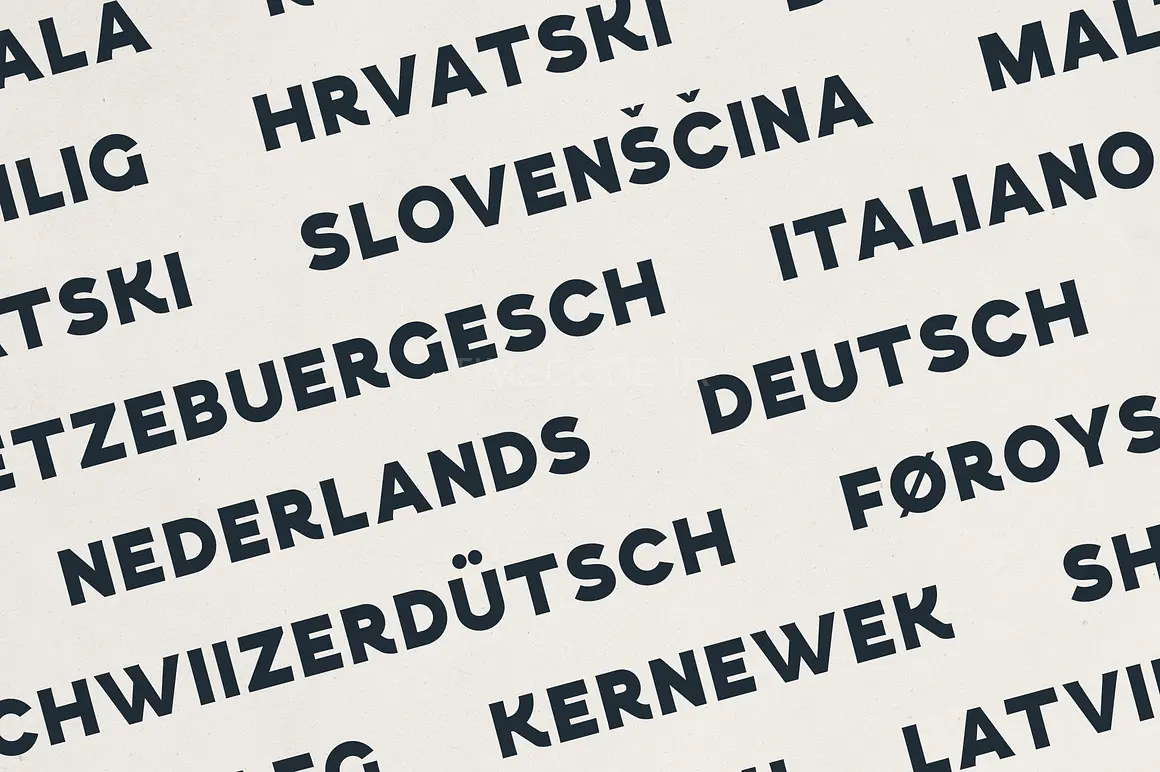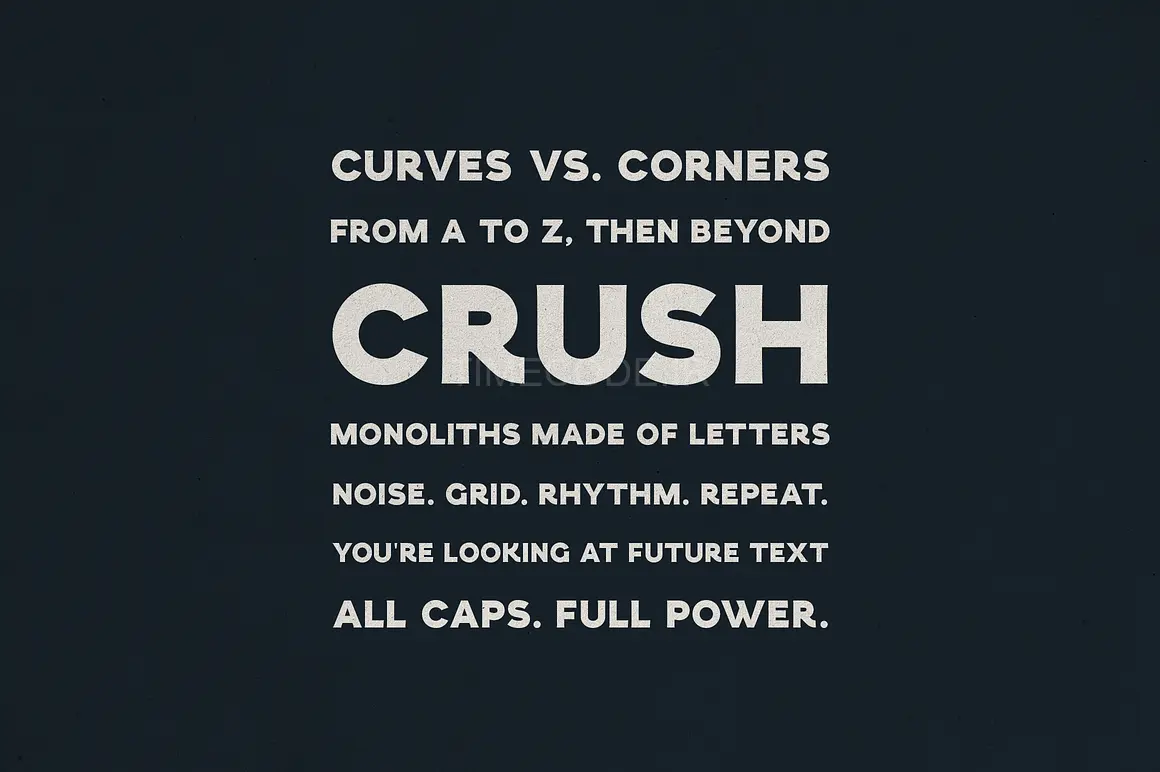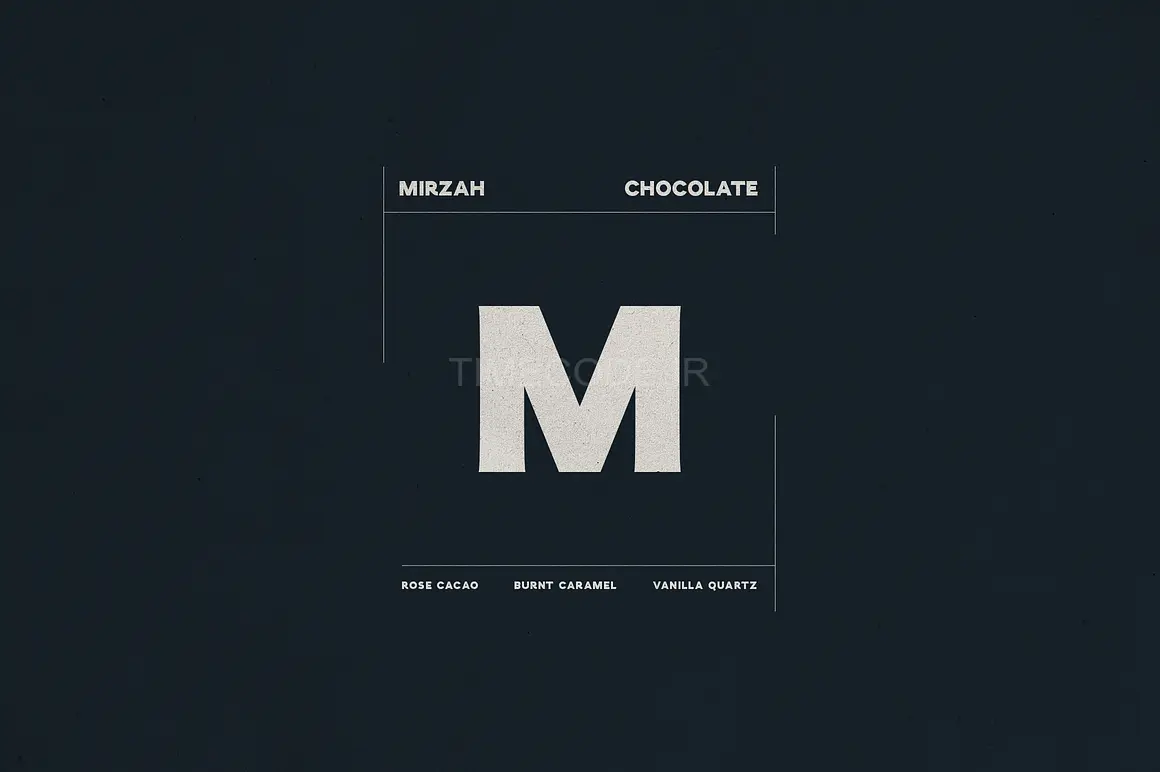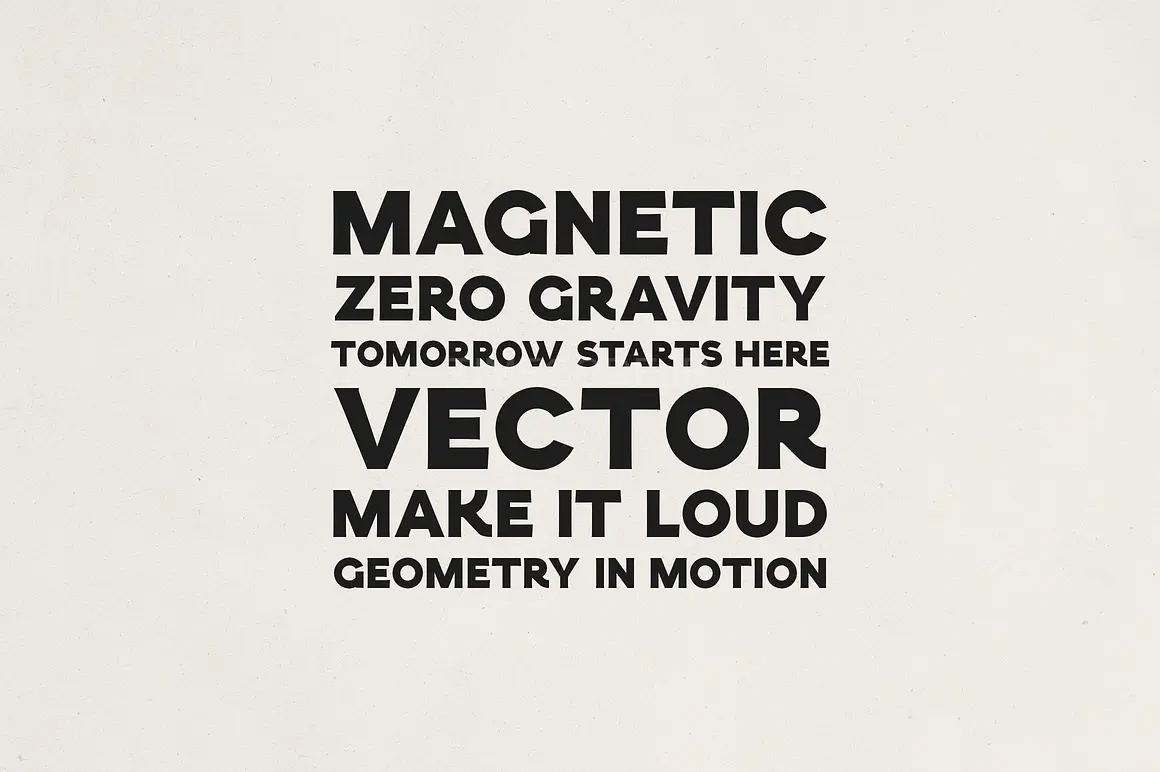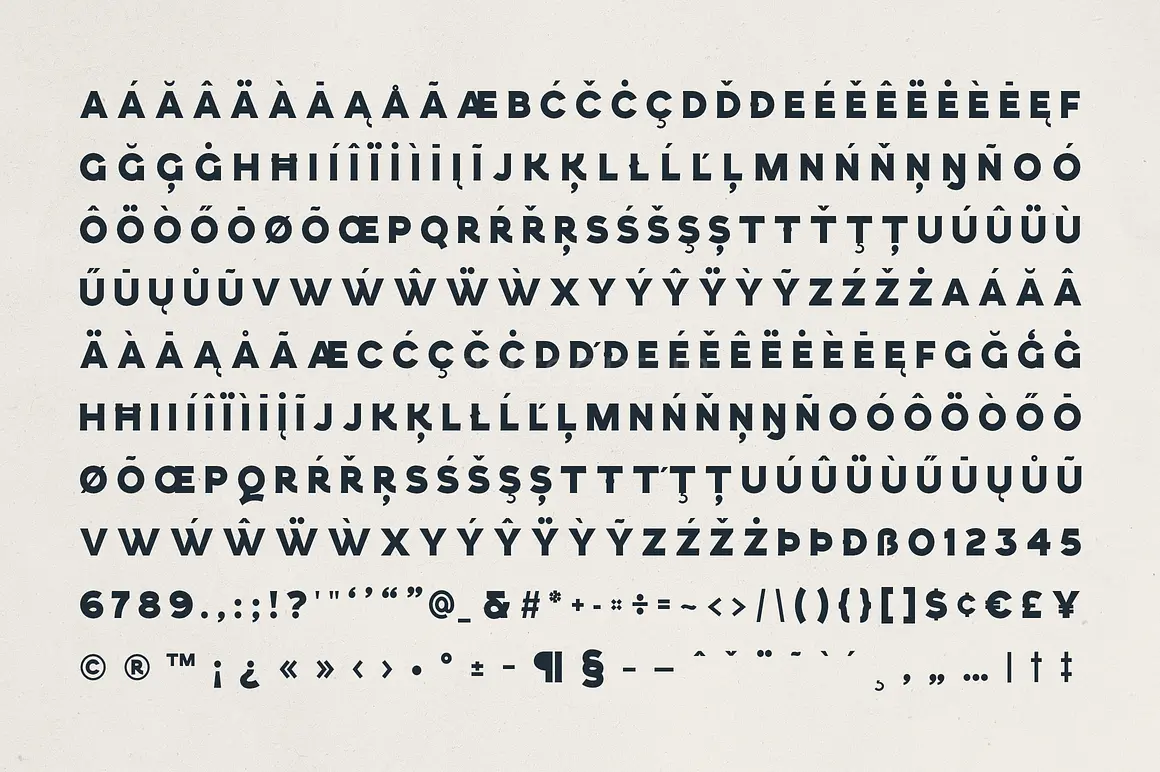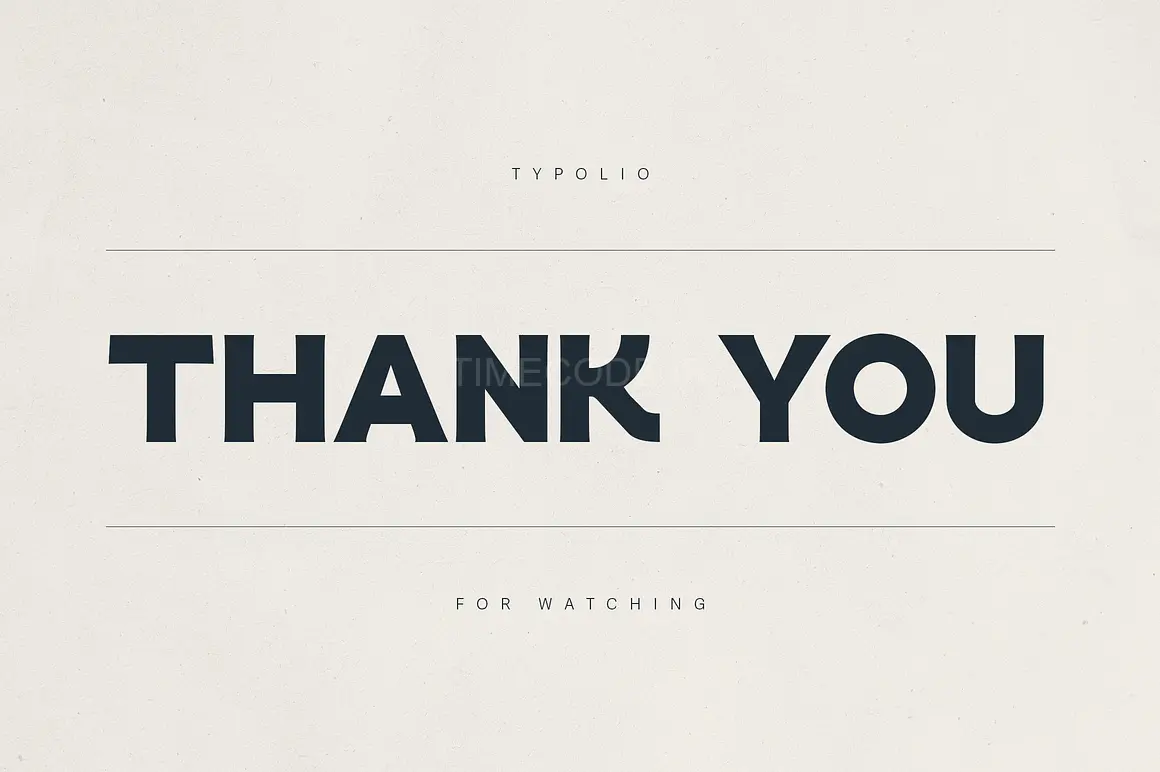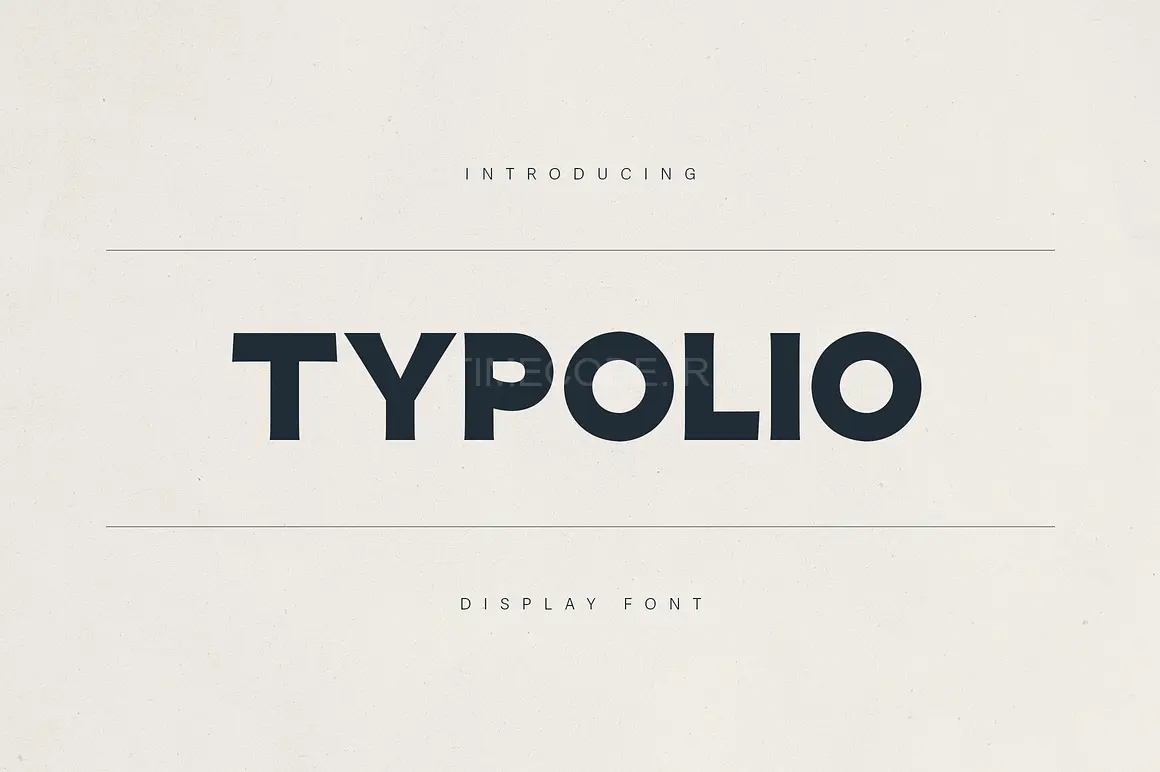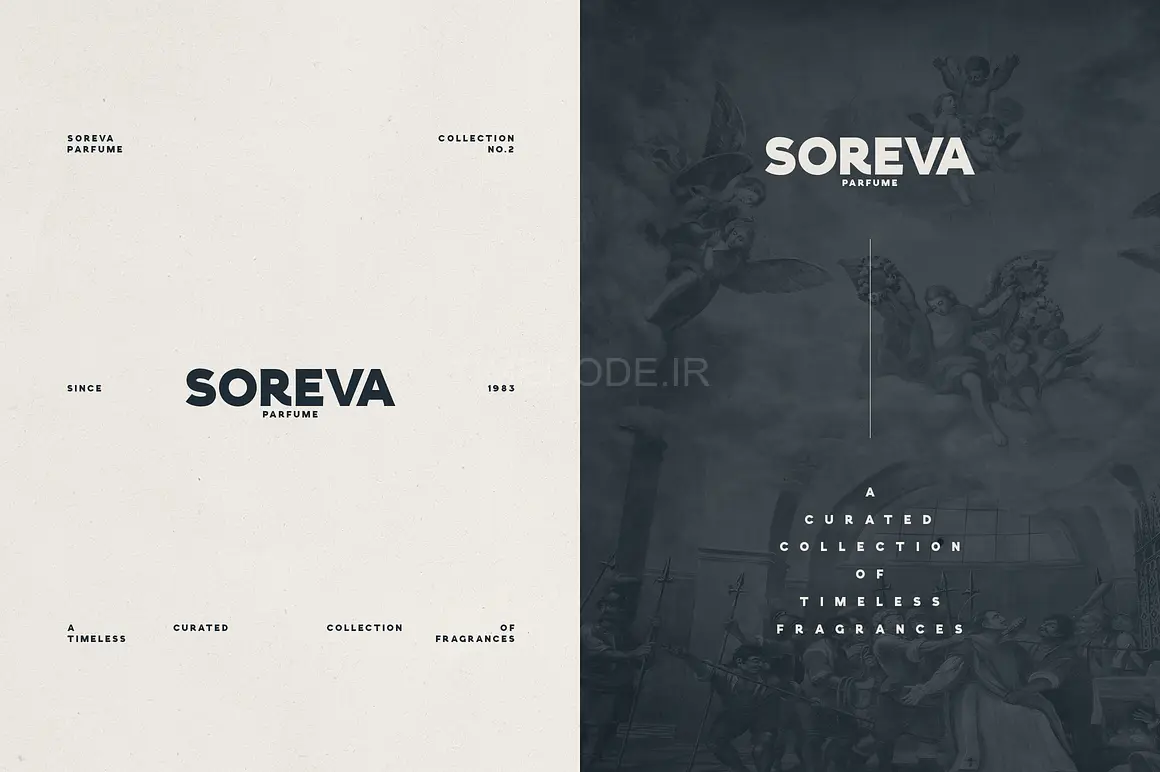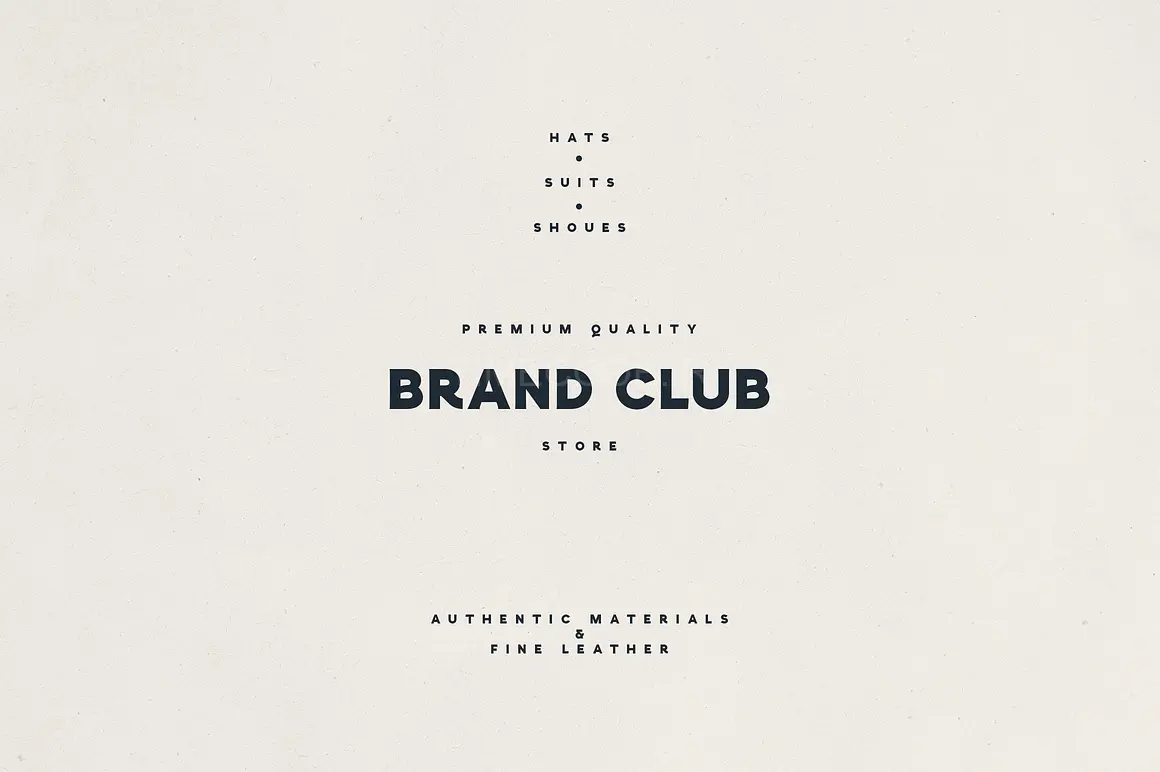
Typolio فونت نمایشگر جسور برای برندهای مدرن. یک فونت نمایشگر همه‌کاره و تأثیرگذار است که برای برندسازی جسورانه، سرفصل‌های مجلات، بسته‌بندی، و پروژه‌های طراحی معاصر طراحی شده است. Typolio با ساختار هندسی قوی و خطوط تمیز خود، سادگی مدرنیستی را با زیبایی‌شناسی سطح بالا ترکیب می‌کند – مناسب برای لوگوها، پوسترها، لیبل‌های مد، استارتاپ‌های تکنولوژی، و طرح‌بندی‌های مینیمالیستی.
چه در حال طراحی یک برچسب عطر، یک برند شکلات لوکس، یا یک خط لباس شیک باشید، Typolio بدون از بین بردن ظرافت، حضور و وضوح را اضافه می‌کند. این تایپ‌فیس برای هر دو محیط دیجیتال و چاپی بهینه شده و خوانایی و شخصیت را در تمام پلتفرم‌ها ارائه می‌دهد.
ویژگی‌ها:
• فقط شامل حروف بزرگ لاتین (All-caps)
• سبک sans-serif تمیز و مدرن
• ایده‌آل برای برندسازی، بسته‌بندی، مجلات و تابلوها
• پشتیبانی از چندین زبان
Typolio – Bold Display Font for Modern Brands
Typolio is a versatile and impactful display font crafted for bold branding, editorial headlines, packaging, and contemporary design projects. With its strong geometric structure and clean lines, Typolio blends modernist simplicity with high-end aesthetics—perfect for logos, posters, fashion labels, tech startups, and minimalist layouts.
Whether you're designing a perfume label, a premium chocolate brand, or a sleek apparel line, Typolio adds presence and clarity without sacrificing elegance. This typeface is optimized for both digital and print, offering readability and character across all platforms.
Features:
• All-caps Latin alphabet
• Clean, modern sans-serif style
• Perfect for branding, packaging, magazines & signage
• Supports multiple languages
Make a statement with confidence—Typolio is typography that speaks loud and clear.
Language Support : Afrikaans, Albanian, Asu, Basque, Bemba, Bena, Breton, Chiga, Colognian, Cornish, Czech, Danish, Dutch, Embu, English, Estonian, Faroese, Filipino, Finnish, French, Friulian, Galician, Ganda, German, Gusi,i Hungarian, Indonesian, Irish, Italian, Jola-Fonyi, Kabuverdianu, Kalenjin, Kamba, Kikuyu, Kinyarwanda, Latvian, Lithuanian, Lower Sorbian, Luo, Luxembourgish, Luyia, Machame, Makhuwa-Meetto, Makonde, Malagasy, Maltese, Manx, Meru, Morisyen, North Ndebele, Norwegian, Bokmål, Norwegian, Nynorsk, Nyankole, Oromo, Polish, Portuguese, Quechua, Romanian, Romansh, Rombo, Rundi, Rwa, Samburu, Sango, Sangu, Scottish, Gaelic, Sena, Shambala, Shona, Slovak, Soga, Somali, Spanish, Swahili, Swedish, Swiss, German, Taita, Teso, Turkish, Upper, Sorbian, Uzbek (Latin), Volapük, Vunjo, Walser, Welsh, Western Frisian, Zulu